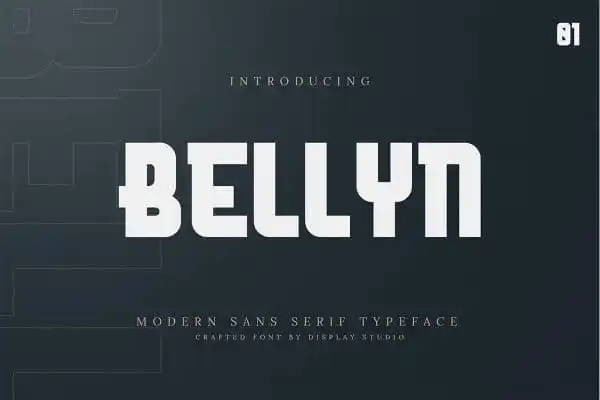
A Bellyn Display Font é uma opção incrível para quem busca destaque visual. Esta tipografia robusta e quadrada traz um forte impacto ao seu trabalho. Foi criada pela Display Studio, a famosa casa de design de fontes. É perfeita para criar logotipos de marcas, cartões de convite, cartas de cumprimento ou qualquer projeto que precise de um toque chamativo e sofisticado. Além disso, seu multilinguismo e variedade de estilos garantem que a Bellyn Display Font seja uma escolha versátil. Ela não só se adapta a diversas línguas ao redor do mundo, mas também oferece diferentes formas para personalizar o design da maneira mais criativa possível. Para qualquer profissional gráfico ou designer de marcas em busca de elementos visuais atemporais e modernos, esta fonte é uma ótima escolha. Ela adicionará elegância e destaque a qualquer trabalho que você trabalhe, garantindo assim um resultado final impecável e diferenciado.